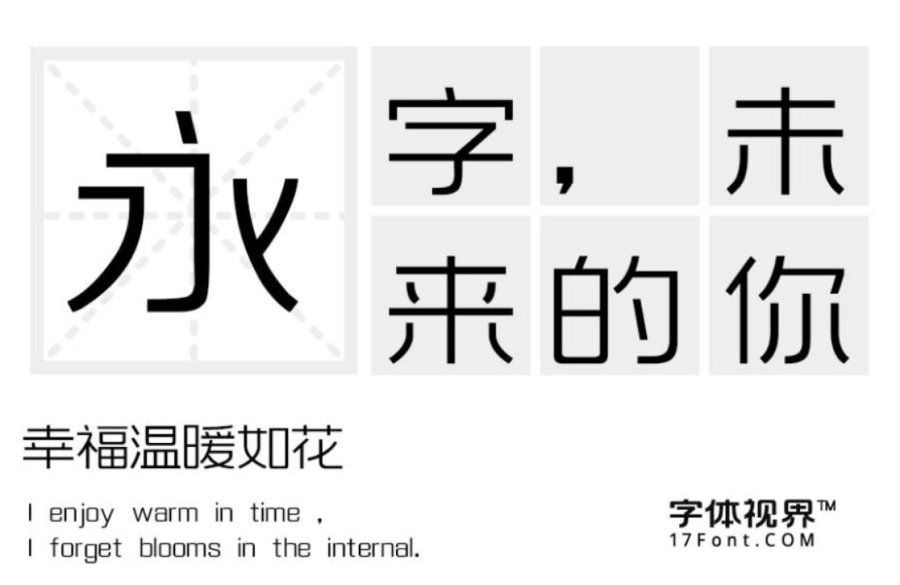
上首方圆体发布
字体名称:上首方圆体
字体类别: 方圆体
适用场景:标题、正文、印刷、屏显、设计
上首方圆体简介:上首方圆体,字体整体特征呈方圆形,笔画粗细匀称,字体下方转角处作圆角处理,字体辨识度高,笔画圆润流畅,看起来软萌可爱,带几分童趣,没有攻击性,给人舒适随和的感觉。适用于儿童产品、娱乐性较强的场景。
上首方圆体预览图展示: